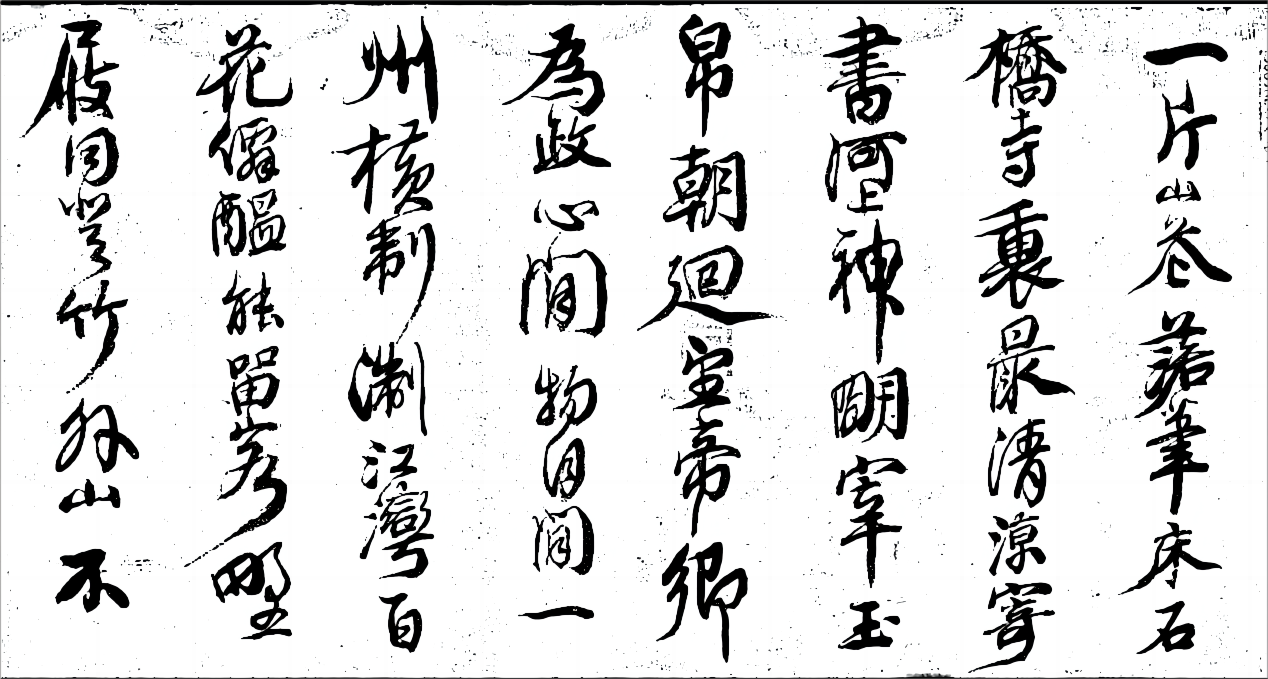
关于汉标查继佐诗卷 字体字库信息
字体全名: 汉标查继佐诗卷
字体简介: 1、下载须知:本字库非标准GB2312字库。本字库只包含了真迹书法原稿中的部分字体。字数的多少取决于原稿的字数的多少。如果有明白的请先联系字觅客服咨询。 2、作品简介:汉标查继佐诗卷是一款根据查继佐诗卷经过再次调整制作的小字库, 此书是查继佐自集唐诗十二首为老师祝寿而作,当中每一首七言绝句都是从四首唐诗中分别选取一句,组合成为一首。整件作品共涉及36位唐代诗人的48首诗, 如岑参、王昌龄、白居易、高适、杜甫、李商隐、刘禹锡、温庭筠、杜牧等人的诗作。个别字句与原诗略有出入。其书学颜真卿,用笔劲健、爽利,分间布白极其匀称。查家在清初遭受了文字狱之灾,当时保存查氏墨迹可能会引起杀身之祸,所以查继佐的传世作品较少,此件则更为珍贵。 3、创作过程说明:汉标查继佐诗卷是作者根据搜集到的真迹图片,于2022年5月13日开始运用抠图、处理背景图,运用造字软件经过再次调整,增减笔画轮廓及修复笔画缺失,调整书法文字比例结构,把每个文字调整到最佳使用效果将410个汉字逐字编码代入模板,在2022年7月20日完成小字库制作。 4、独创性说明:汉标查继佐诗卷小字库的出现,在全国字库界独树一帜,对于中国古代书法艺术的传承具有划时代意义,并且通过把古代名家书法作品调整字体笔画基本位置,合理布局,提高清晰度,去除笔画边缘毛刺及脏点,纠正错别字,均衡整体文字的大小,再次创作而制作成现代字库,让更多书法爱好者能够通过电脑打字使用,真正感受到古代名家书法之美。并且也可以在各种场景下应用。
所属分类: 行书毛笔字手写体书法